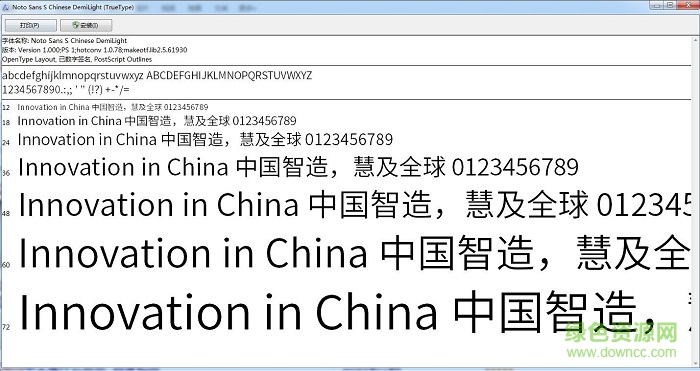
notosanshans-demilight.ttf字體
notosanshansdemilightgbpceuch字體是一款較細(xì)的思源黑體字體,干凈簡潔沒有襯線裝飾,清晰度高,閱讀性良好,實(shí)用性強(qiáng),有需要者歡迎在綠色資源網(wǎng)下載!
黑體字體釋義
1.在中文字體中常用“黑體”;
2.在西文中常用“無襯線體”的稱呼;
3.在日文中被稱為Goshikku-tai(直譯即“哥特體”)。
notosanshans demilight